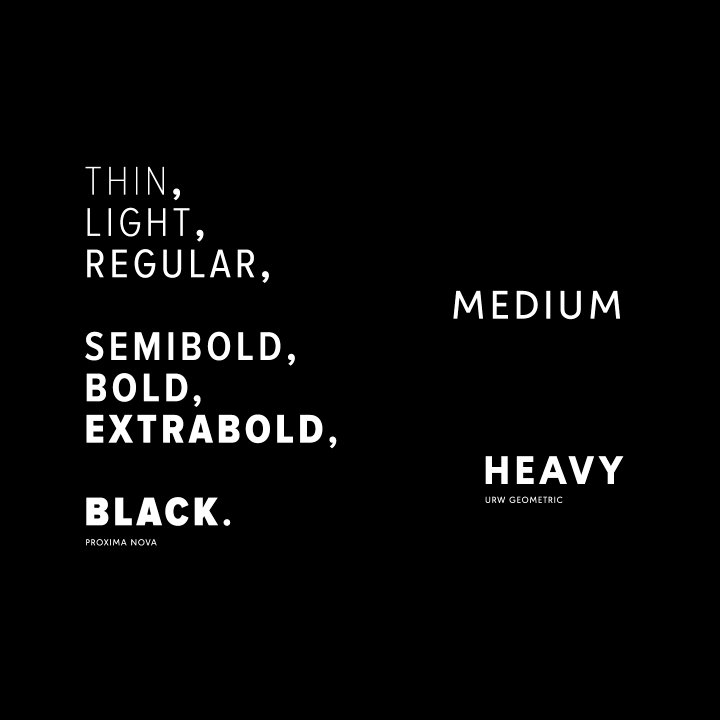
「Pro」ってなに?フォントについて知っているようで知らないホントの意味【まとめ】
日常的にさまざまなフォントを使いわけているWebクリエイターは多いでしょうし、特にデザインに関わる人なら、お気に入りのフォントや「ここぞ」という時のフォント、飛び道具的なフォントなど各種フォントの引き出しを持っている方もいらっしゃるかもしれませんね。
でも「フォントについているあの言葉の意味は?」と聞かれたらいかがでしょうか。なんとなく法則性みたいなものがありそうな感じはしていても、詳しい意味までは知らない方が多いのではないでしょうか?
そこでこの記事ではあまり知られていないフォントに関する言葉の意味をおさらいしましょう。意味がわかれば法則性がより見えやすくなりますので、膨大なフォント群の中から最適なものを選択するスピードがアップしますよ!
Thin, Light, Regular, Medium, Semibold,
Bold, Extrabold(EB),Ultra Bold(UB),
Heavy,Blackなどの意味
これらはフォントのウェイト(weight:太さを相対的に示すもの)やスタイル(個々の用途に合わせて作ったバージョン)に関するものです。そしてウェイトは字の「高さに対する割合」によって定義されます。
「Regular」・・・12-15%
「semi-bold」・・・16-20%
「Bold」・・・25%
これらよりさらに割合の高いエクストラライト(EL)やエクストラボールド、ウルトラボールドなど様々な種類が派生しています。
Book, Regular and Normalの意味
「Normal」は「Regular」の別名なので意味合いは同じです。そのフォントを作った人によって呼ばれ方が変わります。一方、あまり見かけませんが「Book」は可読性が特に高く、「Regular」よりも若干細いスタイルを指します。
オブリークvsイタリック
両方とも斜体ではあるのですが、オブリーク(Oblique)は一般的に電子計算に基づきに傾けたものを指し、イタリックはフォントデザイナーが個々の文字を傾けたものを指し、筆記体など続け書きをする書体では特にフィットします。
ゴシック体とは?
「ゴシック体」は字間が広く、また明朝体のように細い箇所と太い箇所のコントラストがない書体のことを指します。海外では「グロテスク体」と呼ばれるものがありますが、こちらよりも字間が広いことが多いです。
「Pro」の意味とは?
「Pro」がつけられている書体は字間が広いのが特徴であり、オープンタイプフォント(MacとWindows双方で利用できるもの)を指します。国際的なサイトで使われたり、タイポグラフィで使われるのに適しています。
フォント名につけられている「mono」の意味って?
「mono」は通常モノスペースフォントのことを指します。つまり文字の横幅がすべての文字で同じに統一されているフォントのことです。
まとめ
以上、あまり知られていないフォントにまつわる語の意味をご紹介しました。
ちなみに余談ですが、この記事を書きながらPhotoshopにデフォルトで入っているフォントタイプを眺めていたのですが、「エクストラボールドレギュラー」というフォントを発見してしまいました……。
これってボールドなの?それともレギュラーなの……?
フォントの種類は実に多岐にわたっていますね。